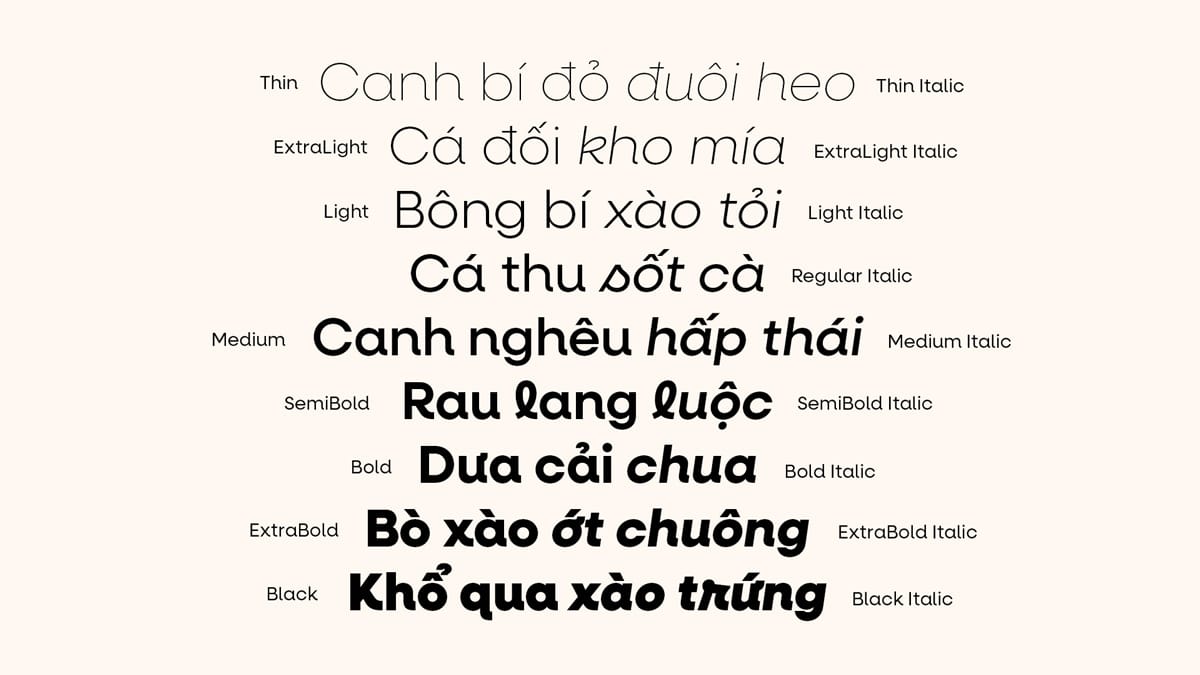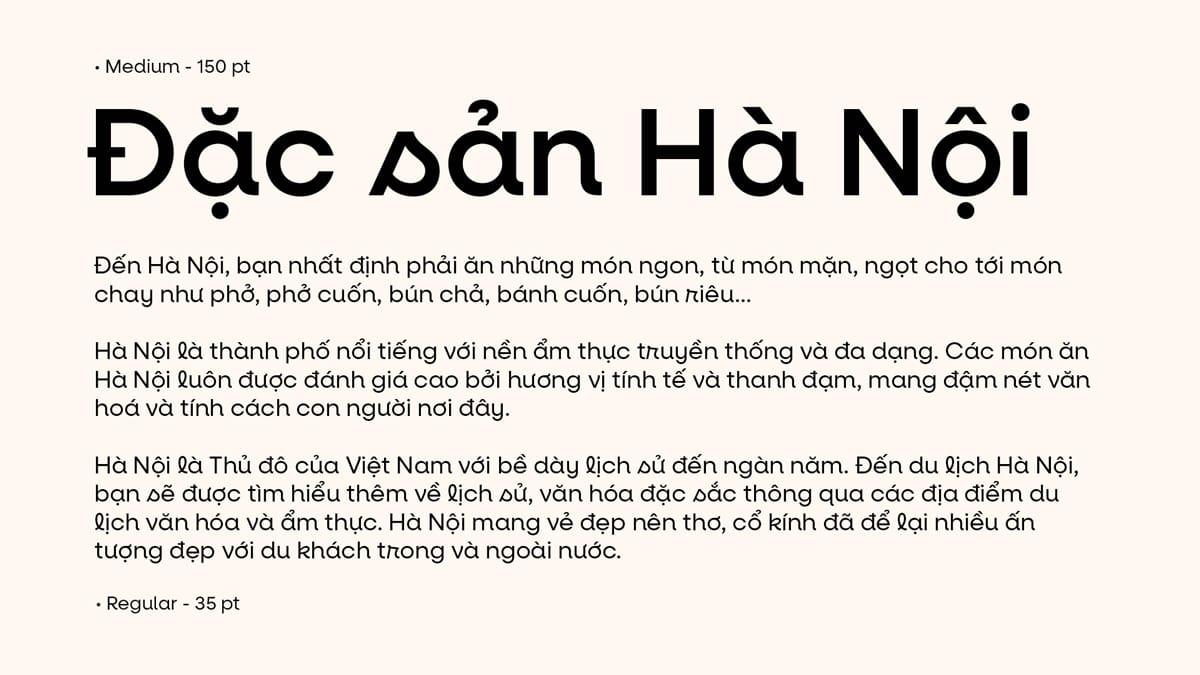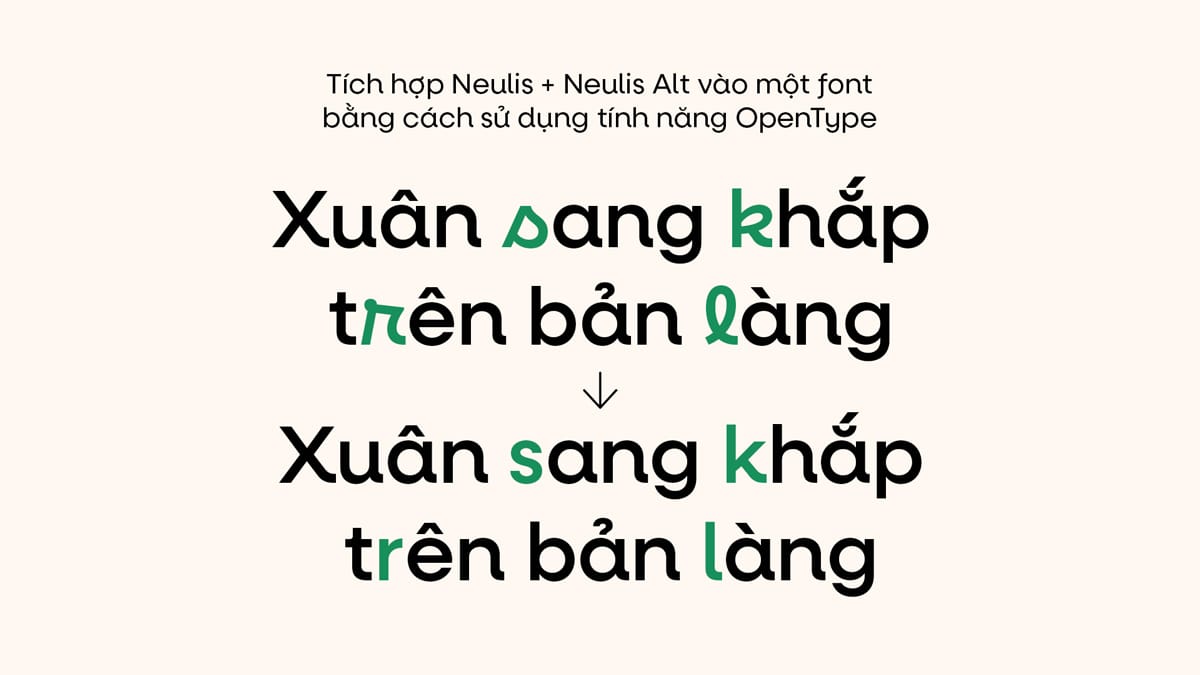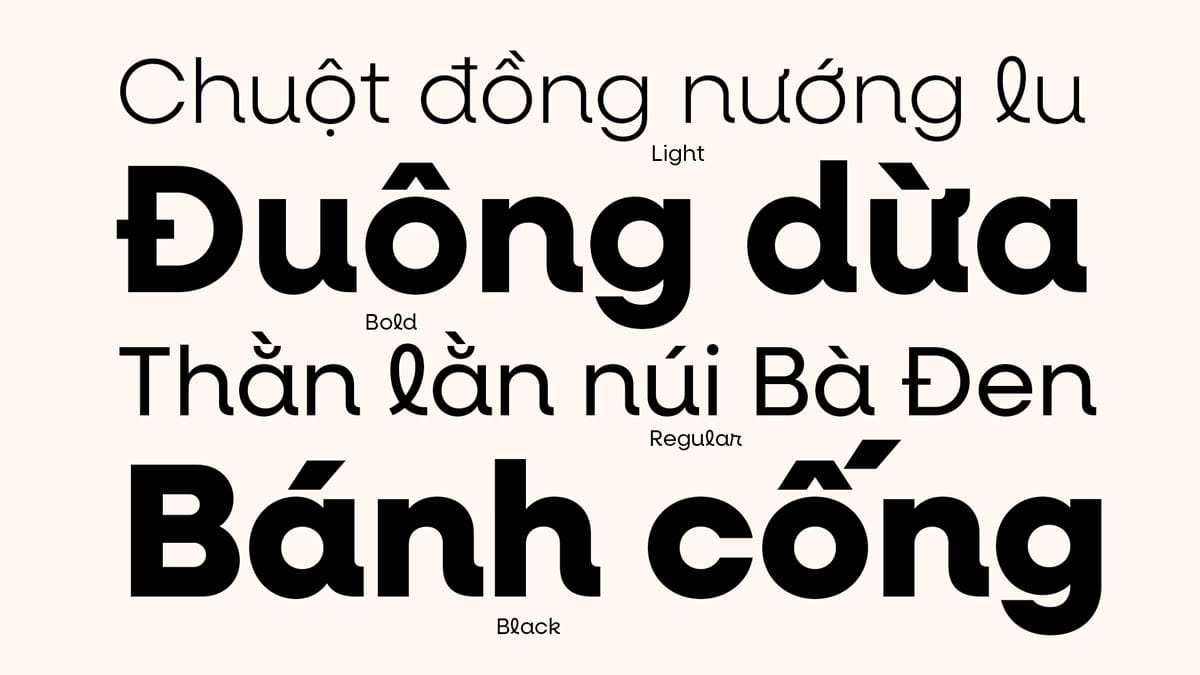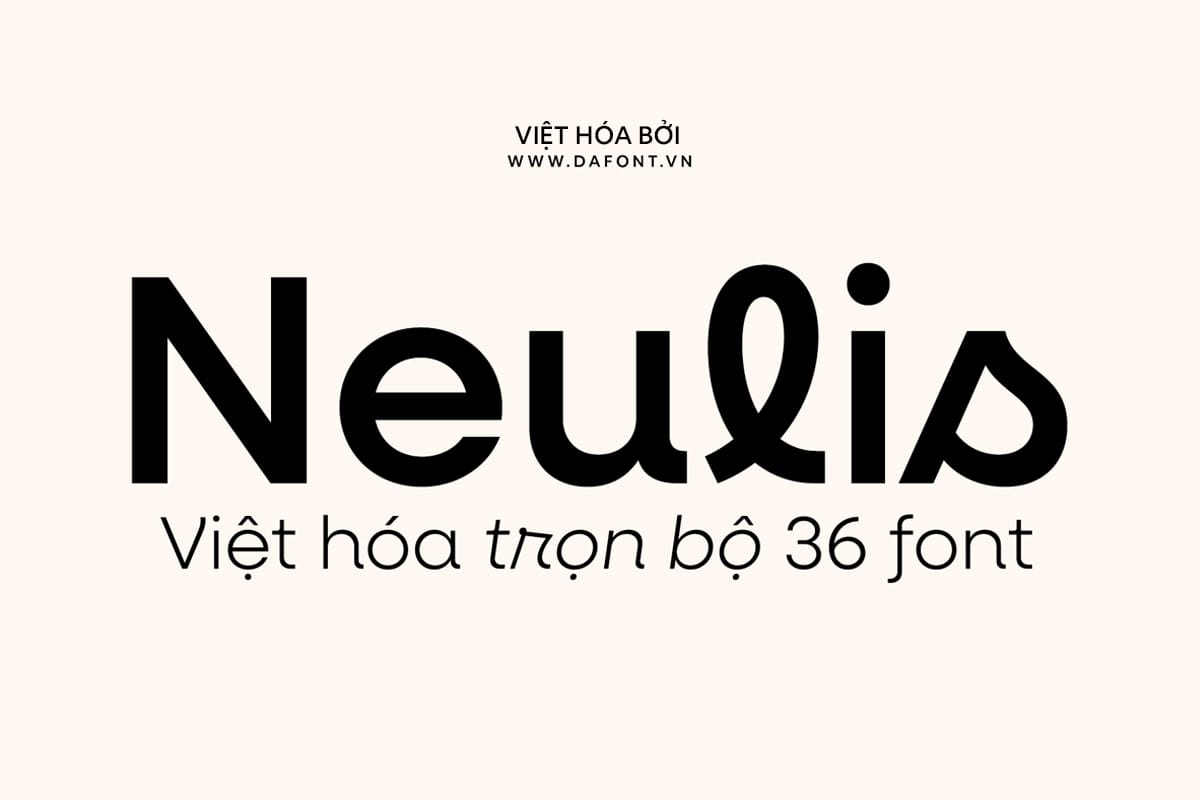
DFVN Neulis là một font chữ kết hợp giữa sans serif hình học và chữ viết hiện đại với hai biến thể khác nhau.
Thiết kế của Neulis mang đến một hiển thị độc đáo của các ký tự được lấy cảm hứng từ các dạng chữ viết tay (bao gồm ký tự l, k, r, s) cùng với các nét kết thúc kiểu chữ viết (như a, n, u) hòa quyện vào cấu trúc hình học tổng thể của kiểu chữ. Thiết kế của Neulis Alt cung cấp một lựa chọn đơn giản hơn bằng cách giữ lại các dạng chữ sans serif cổ diển.
Với diện mạo monoline, kiểu chữ với vẻ ngoài hiện đại. Hai lựa chọn có thể được kết hợp với nhau để phù hợp với nhu cầu sử dụng trong cả hiển thị và văn bản. Neulis mang đến một kiểu font chữ độc đáo và phù hợp cho rất nhiều thiết kế khác nhau như xây dựng thương hiệu, quảng cáo, bao bì sản phẩm, tiêu đề, tạp chí, trang web, logo và nhiều hơn thế.
DFVN Neulis bao gồm nhiều tính năng:
- Normal and Alt families
- Swash capitals (PUA-encoded)
- Stylistic alternates (J, M, Q)
- Case-sensitive punctuation for All Caps
- Arrows
- Fractions, numerators, denominators
- Superscript, subscript
Nhà thiết kế: Adam Ladd
Việt hoá: DFVN
Để việc sử dụng được dễ dàng và tối ưu hơn, bộ font Neulis và Neulis Alt đã được tích hợp thành một, bạn có thể sử dụng tính năng OpenType để chuyển đổi qua lại.
DFVN Neulis (kèm Neulis Alt) là bộ font sans-serif Việt hóa hiện đại, linh hoạt và dễ dùng cho nhiều mục đích thiết kế. Với nhiều độ đậm và biến thể chữ, font được tối ưu để hiển thị rõ ràng cho cả tiêu đề (display) và văn bản (text), rất hợp cho UI/UX, branding, poster, social và ấn phẩm truyền thông.